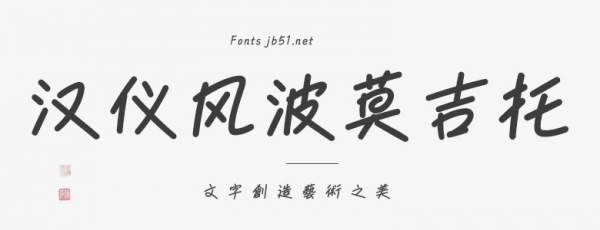
漢儀風(fēng)波莫吉托是一款具有獨(dú)特藝術(shù)風(fēng)格的字體,筆畫(huà)流暢自然,富有動(dòng)感和節(jié)奏感。線(xiàn)條的粗細(xì)變化豐富,能展現(xiàn)出獨(dú)特的韻律。整體風(fēng)格較為優(yōu)雅,具有一定的文藝氣息,同時(shí)又不失現(xiàn)代感。適用于海報(bào)、宣傳冊(cè)、包裝等設(shè)計(jì)領(lǐng)域,能夠?yàn)樽髌吩鎏愍?dú)特的視覺(jué)效果。